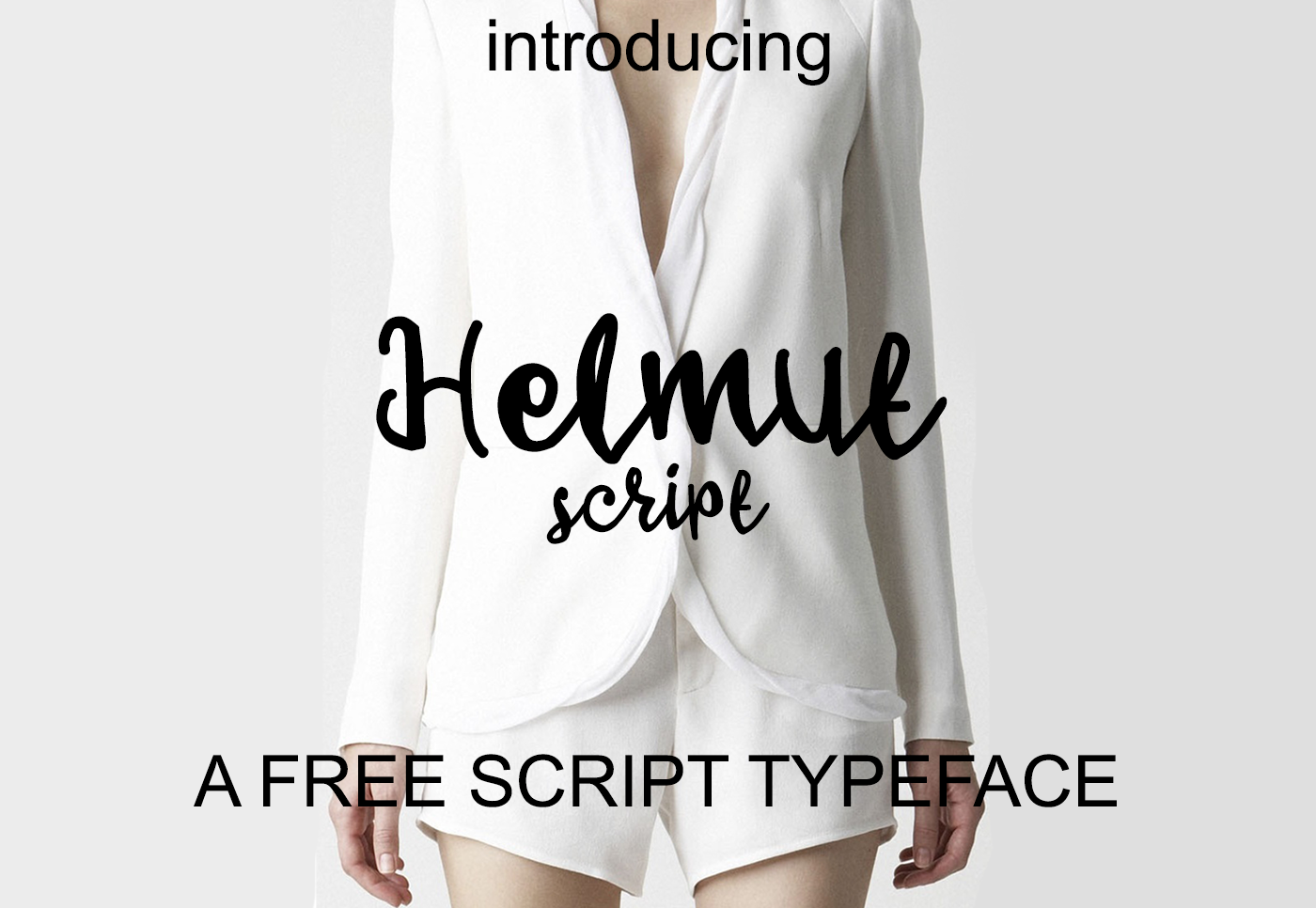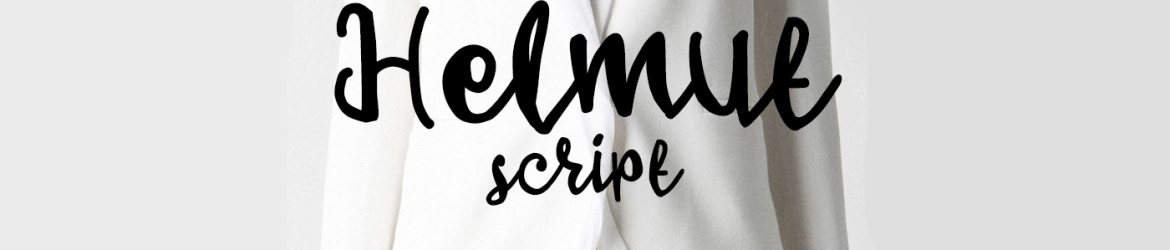
Helmut Script Font – Download Grátis
A Helmut Script é uma fonte script que apresenta características elegantes e diferentes para se tornar o ponto forte de qualquer projeto visual. Introduzida pela Polythene Designs, esta fonte foi criada pelo designer Hamilton. Ideal tanto para projetos de marca como para a criação de logotipos, embalagens de produtos ou até mesmo para scrap booking e cartões de convidados, Helmut Script traz uma personalidade única que enriquece qualquer trabalho gráfico. Suave, fluida e versátil, esta fonte é perfeita tanto para criar um toque único em sua identidade visual quanto para dar vida às mensagens mais pessoais e emotivas. Seja em blogs, cartas de cumprimentos ou notícias, a Helmut Script traz uma nuance única à forma como nos comunicamos através da escrita. Com certeza será um recurso gráfico valioso na sua coleção de fontes.